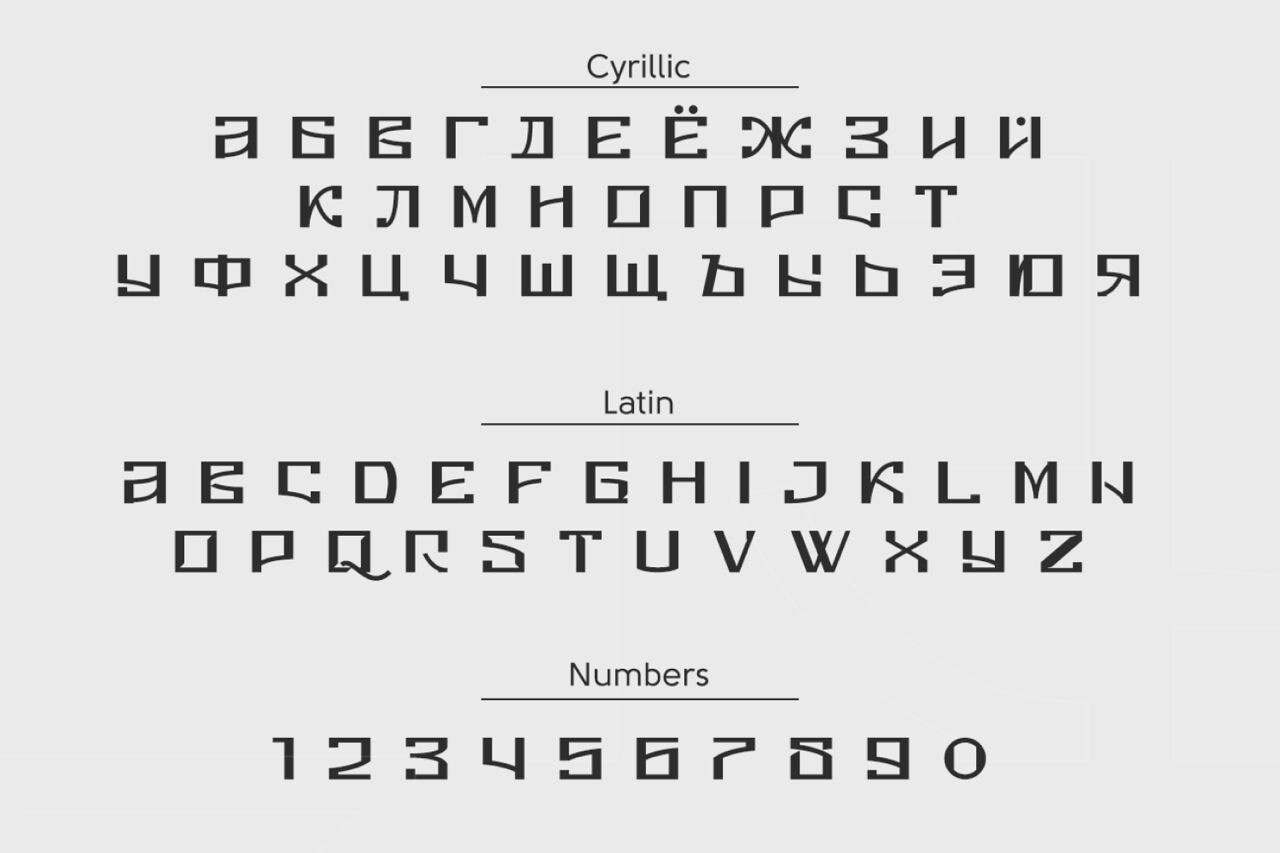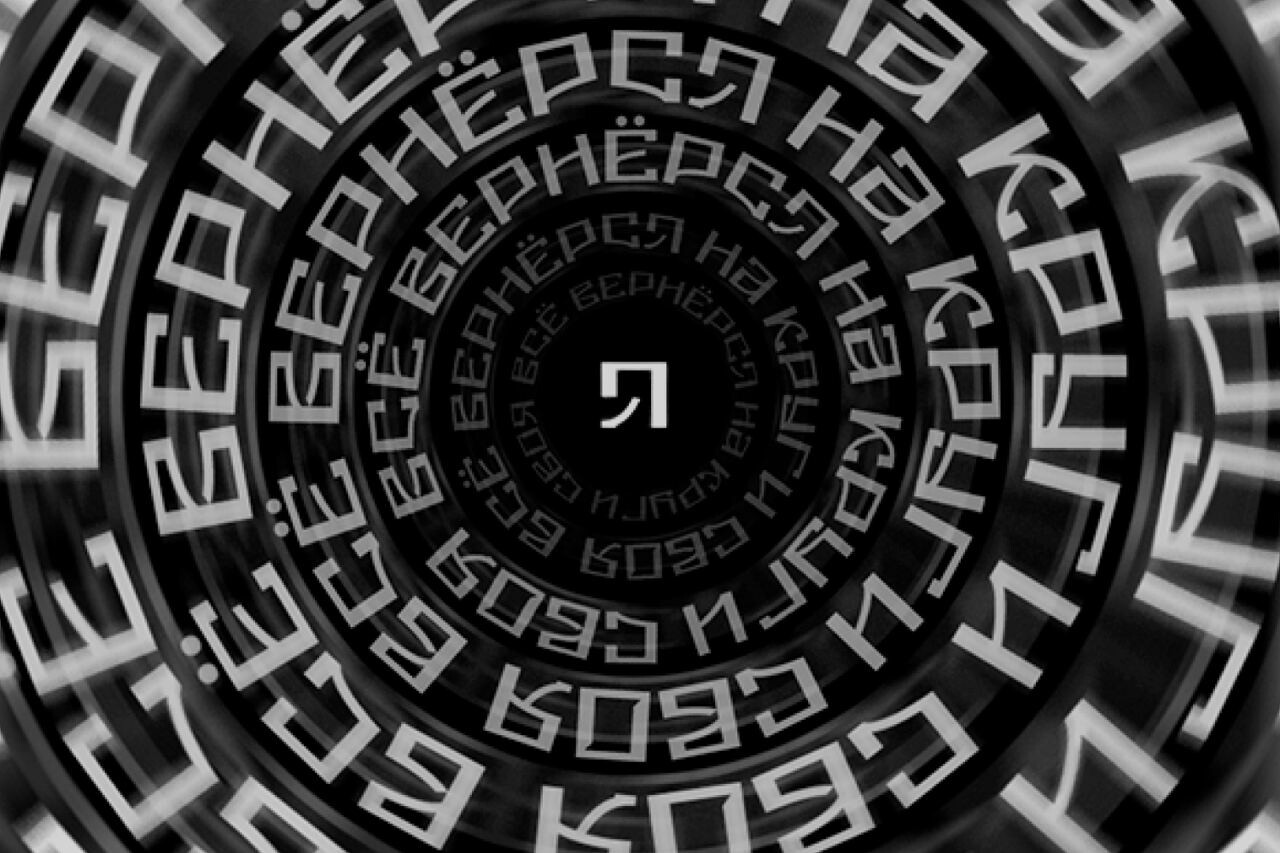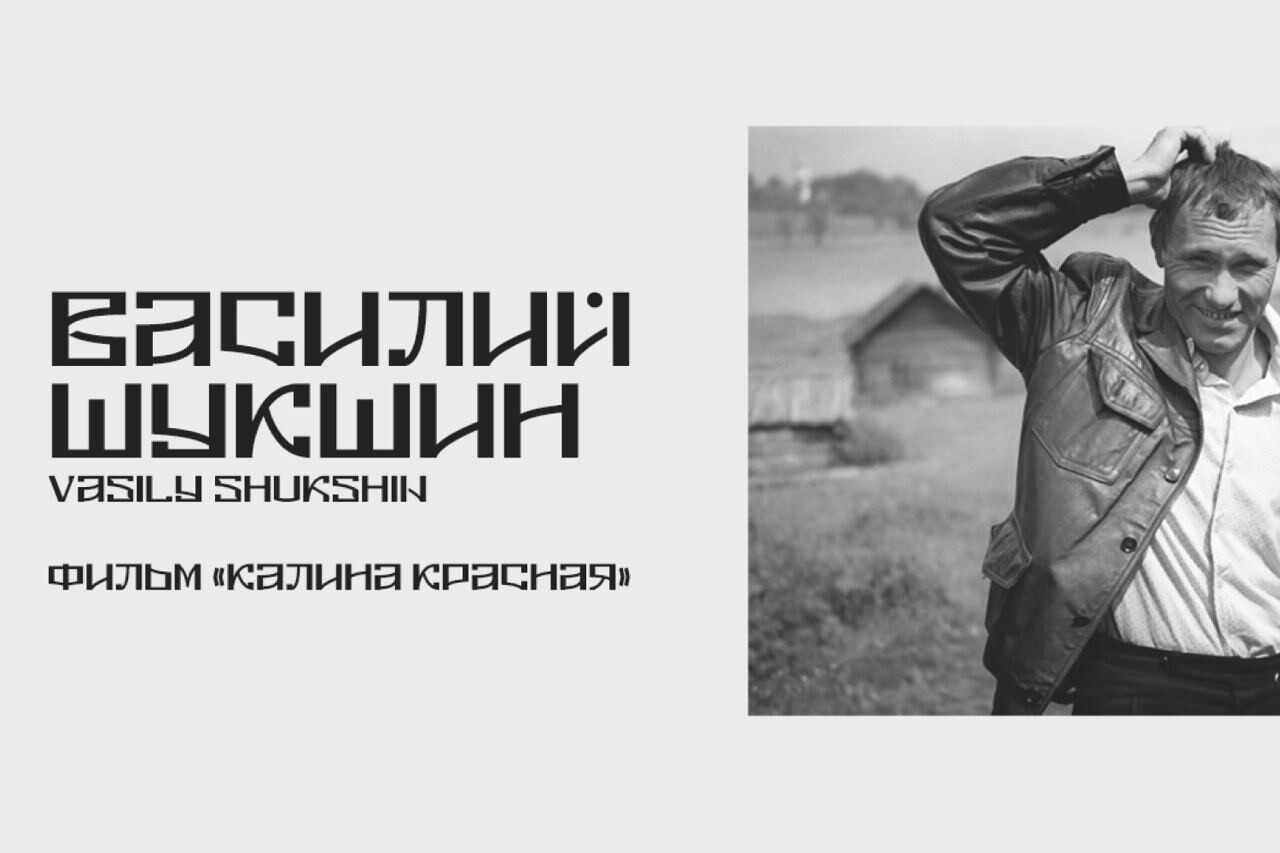
Шрифт Belozersk: мост между современностью и стариной 👍✍️
А что, если современный дизайн вдруг заговорит голосом древнего русского города? Получается Belozersk - шрифт, в котором время будто замирает и одновременно бежит вперёд. Неожиданно, правда? Один дизайнер решил соединить эпохи в буквах - и у него вышло нечто по-настоящему живое.
От автора с душой
"Когда-то мне пришла в голову идея создать шрифт, в котором сочеталась бы современность и старина. И получился Belozersk", - делится Марк Дубоносов. Это его первый шрифт. На него ушло огромное количество времени - целая пропасть, как он сам говорит. И это чувствуется. Каждая линия несёт в себе уважение к прошлому и взгляд в будущее.
Характер и вдохновение
Belozersk - изящный геометрический декоративный шрифт. Он вдохновлён наследием русской культуры и маленьким городом в Вологодской области. Сочетание винтажных мотивов с современными акцентами создаёт особую атмосферу. Как будто старые стены Белозерска вдруг засияли в лучах сегодняшнего дня. Поддерживает кириллицу и латиницу.
Где он заиграет
Belozersk отлично подходит для проектов, где хочется передать глубину и связь времён. Заголовки, брендинг, плакаты - везде, где нужна выразительность. Он не кричит, а рассказывает. Спокойно, уверенно, с лёгким налётом истории.
Иногда первый шаг оказывается самым важным. Belozersk - это не просто шрифт, а целое путешествие от идеи до готовых букв. Он напоминает: настоящее творчество рождается там, где встречаются прошлое и настоящее. И хочется верить, что таких мостов будет всё больше. ✨